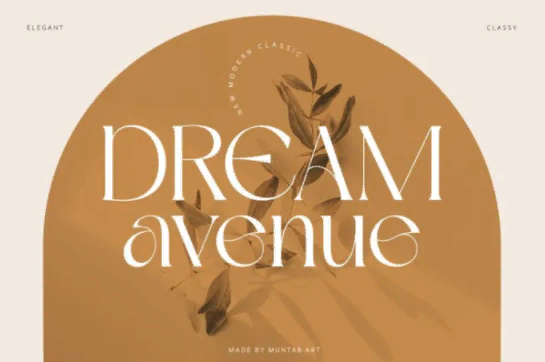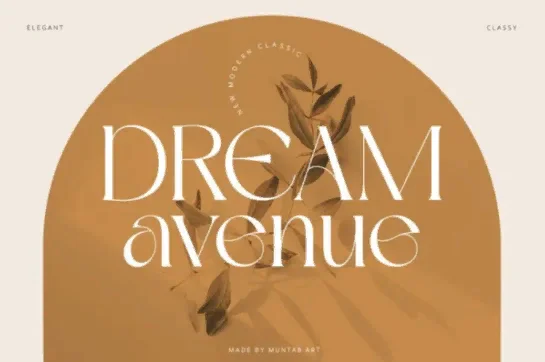
Название: Dream Avenue Font (2021)
Шрифт Dream Avenue включает в себя прописные буквы, строчные буквы, цифры, большой набор знаков препинания.
Шрифт Serif с современным классическим стилем. Создан для плакатов, веб-дизайна, брендинга, иллюстраций, значков и некоторых других работ.